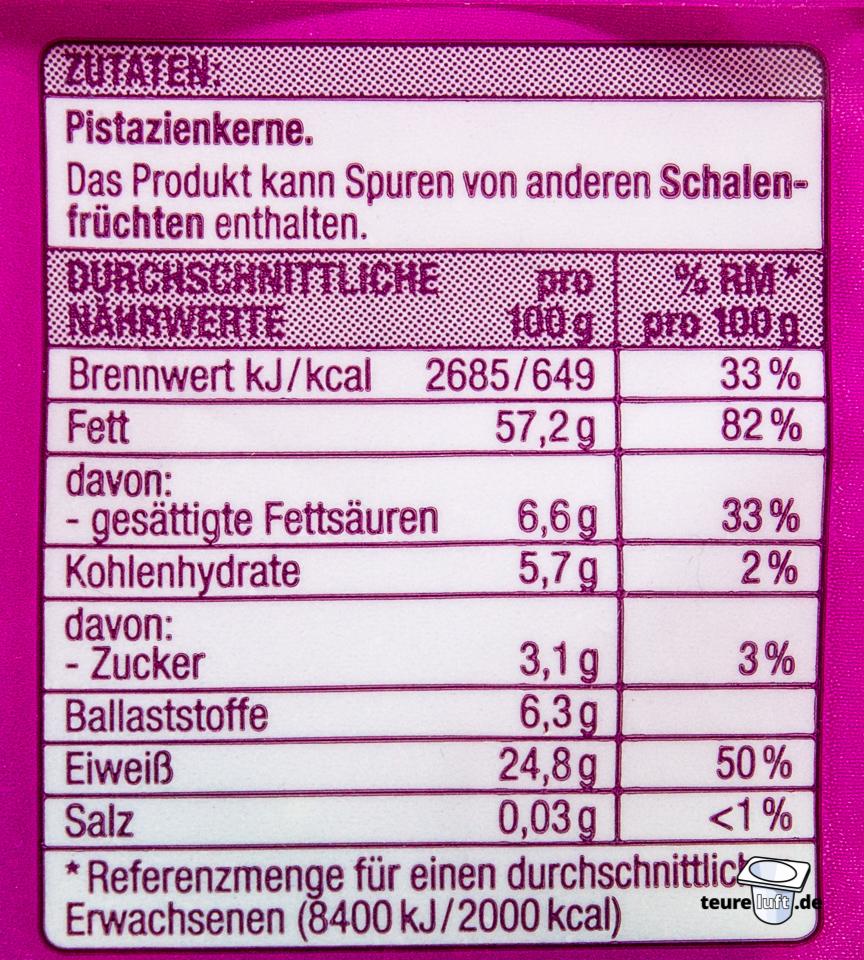
Welche Schrift wird häufig für Nährwerttabellen oder andere Produktinformationen eingesetzt?
ich suche nach dieser recht standardmäßigen oder einer sehr ähnlichen Schrift für Lebensmittelkennzeichnungen. Laut Gesetz ist nur die Mindestschriftgröße festgelegt, jedoch findet man auf vielen Produkten diese serifenlose Condensed-Schrift. Kennt sich jemand aus?
Helvetica Condensed sollte passen.
Vielen lieben Dank! Passt gut. Hatte die Roboto Condensed Regular gewählt, da sie nicht ganz so eng läuft und einen Tick freundlicher wirkt.
ja, die Roboto Condensed sollte auch funktionieren und wirkt nicht ganz so ausgelutscht, außerdem ist die Roboto kostenfrei erhältlich – somit alles richtig gemacht.